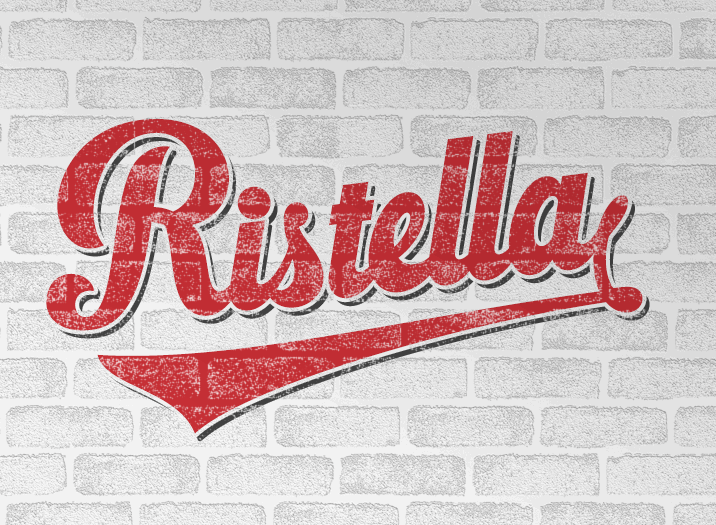
A Ristella Font é uma elegante escolha para quem procura uma escrita a mão única e envolvente. Se você busca um estilo que seja tanto moderno quanto refinado, esta fonte oferece precisão com traços delicados e acabamentos perfeitos. As finas dobras nas letras dão ao texto um ar romântico que não deixa ninguém indiferente. O designer Måns Grebäck trouxe uma mistura única de acabamentos terminais e caudas para criar as famosas “escamas” (swashes) da fonte, encontrando exemplos em símbolos como [ ] { } Tails são descritas pelos sinais < > § _ ¤. Com sua arquitetura cuidadosa e uma variedade de estilos, a Ristella é perfeita para aqueles que buscam dar vida à escrita, tornando-a ainda mais única e pessoal. Seja para gráficos publicitários ou letras digitais, a Ristella oferece um design rico e sofisticado que não apenas atrasa os olhos, mas também o coração.